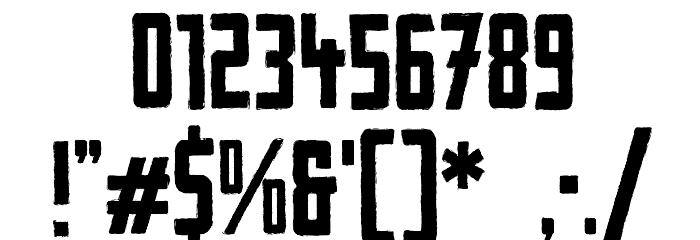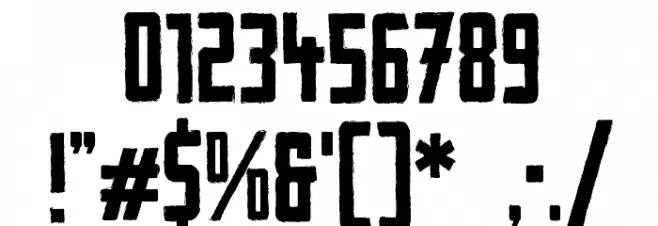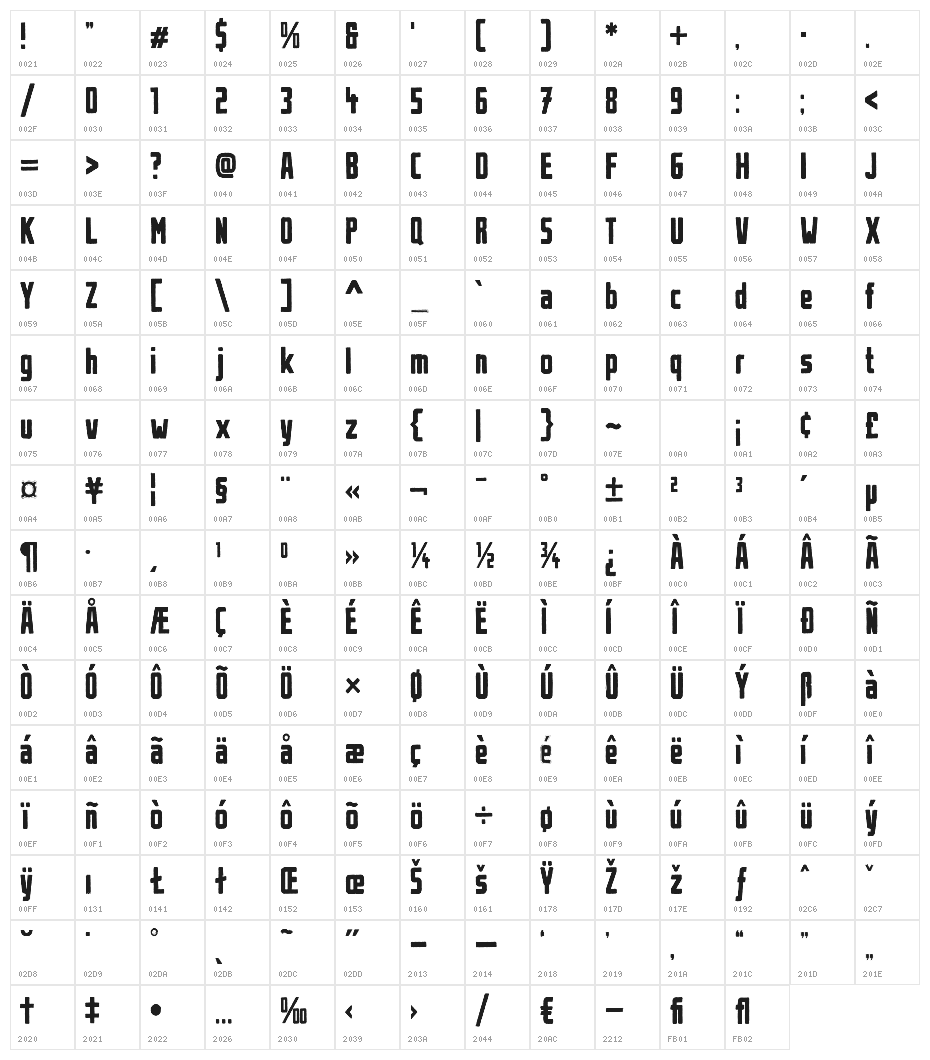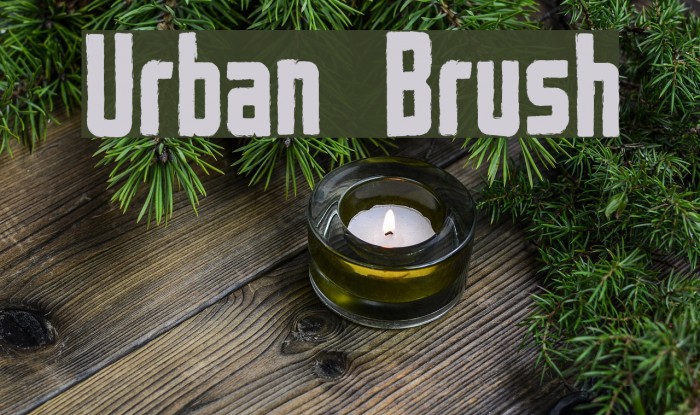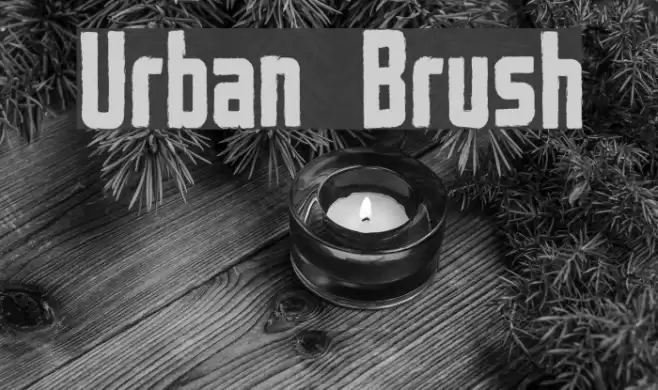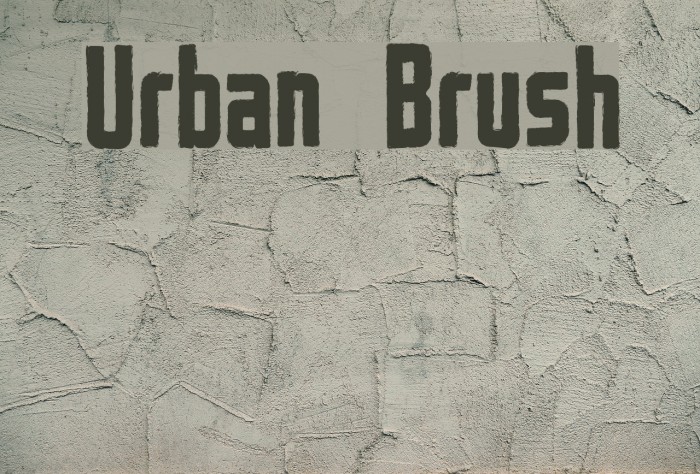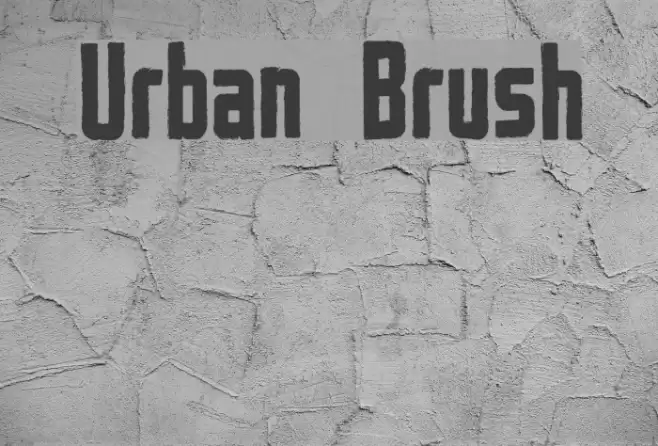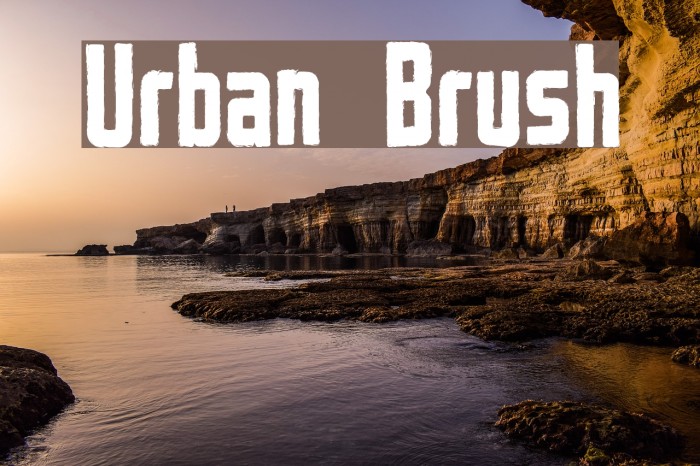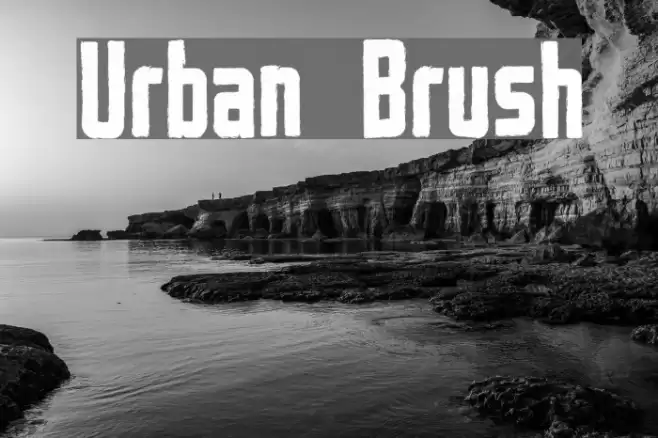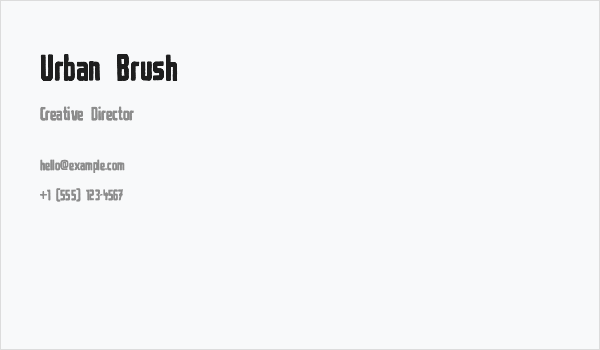
Urban Brush Font
✎ Distorted Eroded
| Estilo geral | Urban, Artistic |
| Projetos propostos | Ideal for street art designs, posters, album covers, and branding that requires a bold, artistic touch. |